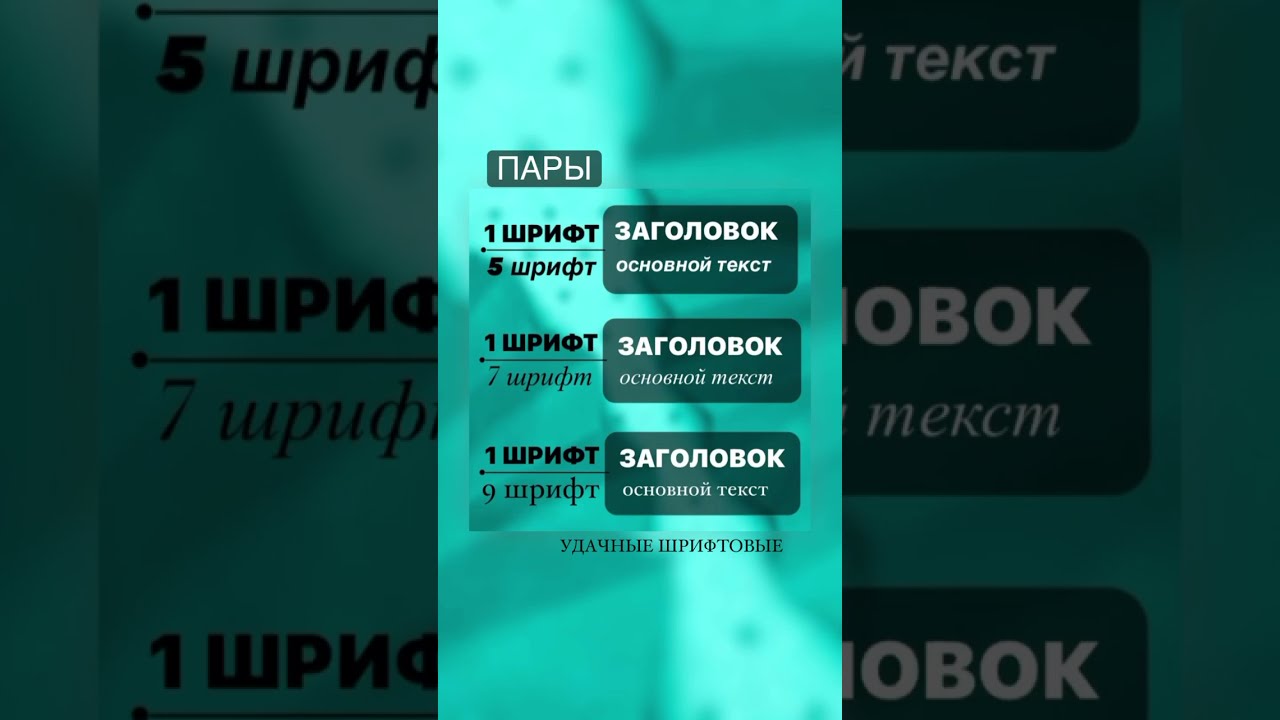
принципы создания идеальных шрифтовых пар
Практически в любом музыкальном треке, где главную роль играет вокал, используется не одна голосовая партия. Иногда на это не сразу обращаешь внимание, но пробирающие до мурашек моменты дублируются другой партией — на тон ниже или выше, чтобы расставить акценты и усилить эффект. Часто такие фрагменты исполняют бэк-вокалисты, чтобы разница тембров подарила слушателю больше эмоций.
Шрифт легко представить голосом, ведь он не только передаёт информацию читателю, но и является источником эмоций. Мы уже писали о том, что голос бренда — это шрифт. Настало время рассказать о том, как усиливать основной голос бренда, используя шрифтовые пары, и как управлять сочетанием гарнитур грамотно, чтобы произвести на читателя нужный эффект.
Более того, на примере создания TT Norms® Pro Serif вы сможете узнать, как шрифтовые пары создаются в рамках одного семейства и где их лучше применять.
Что такое шрифтовая пара?
Не все шрифты будут красиво смотреться в одном проекте.
Дизайнеры знают, что выбрать для проекта даже один подходящий шрифт бывает непросто, а найти идеальную пару — ещё сложнее. Но для начала выясним, что вообще принято называть шрифтовыми парами.
Шрифтовая пара — это сочетание двух шрифтов в одном проекте. Особенность в том, что в таком сочетании у каждого шрифта своя задача. Как правило, один должен привлечь внимание, другой — донести информацию и не мешать прочтению текста. Первой гарнитурой будут оформлены заголовки и выделительные части текста, второй — основной текстовый массив.
Важный фактор состоит в том, что между двумя выбранными шрифтами должна произойти химия, они должны хорошо дополнять друг друга. Иначе магии не случится, и читатель не испытает заложенную брендом эмоцию.
Процесс выбора таких шрифтов творческий. Нет свода правил, который точно определяет, подойдут шрифты друг другу или нет.
Для чего нужны шрифтовые пары
Безусловно, можно использовать один шрифт для бренда, не усложняя задачу поиском пары.
Это самый простой и безопасный путь для дизайнера.
Правда в том, что этот путь не всегда подходящий. Человеческое внимание устроено так, что долго фокусироваться на однообразных вещах ему трудно, нужны зацепки. При чтении такими якорями выступают участки текста, выделяющиеся визуально.
Шрифтовая пара помогает направить внимание читателя. Прочитать заголовок поможет более крупный кегль и выразительный шрифт, отличающийся от того, которым набран массив текста. Выделительные функции в основном объёме текста на себя возьмёт курсив или жирное начертание.
Используя два разных шрифта, вы облегчите задачу аудитории и усилите эмоциональное сообщение бренда.
Принципы сочетания шрифтов
Можно найти десятки статей о шрифтовых парах, но ни одна из них не предоставит чётких правил по выбору шрифтовой пары. За химию между шрифтами отвечает множество компонентов, не все из них поддаются инструкциям.
Однако мы расскажем о создании шрифтовой пары к бестселлеру студии TT Norms® Pro, чтобы после дать рекомендации от студии.
Они помогут в будущем при выборе гармоничного сочетания гарнитур.
Гротеск TT Norms® Pro и антиква TT Norms® Pro Serif
TT Norms® Pro — главный бестселлер студии TypeType. Гарнитура стала голосом брендов Cartoon Network, Sartorius, Intercom, CSN и многих других.
Отчасти популярность связана с тем, что TT Norms® Pro — геометрический гротеск с нейтральным характером. Это универсальный шрифт, современный и стильный, его характер легко адаптировать под разные сферы.
Семейство гарнитуры расширялось несколько раз, дополняясь моноширинной версией TT Norms® Pro Mono, новыми начертаниями и языками. За счёт универсальности подобрать шрифтовую пару к TT Norms® Pro несложно, но студия TypeType решила разработать идеальную пару и создать антикву, которая будет гармонично дополнять гротеск.
Нам хотелось создать не просто дополнение к классической версии, но текстовую антикву, которую дизайнеры смогут использовать самостоятельно или в паре с другими шрифтами.
Мы начали с исследования, в котором изучили крупные шрифтовые семейства других студий и авторов, в которых одновременно присутствовали антиква и гротеск.
В тестовом варианте мы проверяли, насколько похожим на TT Norms® Pro хотим видеть новую антикву.
Финальная версия TT Norms® Pro Serif — это баланс между схожестью характеров и визуальной разницей форм.
TT Norms® Pro — это гротеск со слабым контрастом и умеренным характером. Как вы знаете, антиква отличается засечками и высоким контрастом штрихов, но изменить эти два компонента недостаточно, чтобы создать пару.
Чтобы шрифты сочетались безупречно и между ними появилась химия, необходимо добавить что-то ещё, что сделает антикву действительно самостоятельным шрифтом.
В TT Norms® Pro Serif появились свои характерные черты.
- Шрифт стал жестче. Поменялись влития арок, форма полуовалов.
- Круги знаков остались круглыми, но появилась динамика в овале. В TT Norms® Pro овал симметричен по вертикали, а в TT Norms® Pro Serif в круглых знаках появляется наклон.